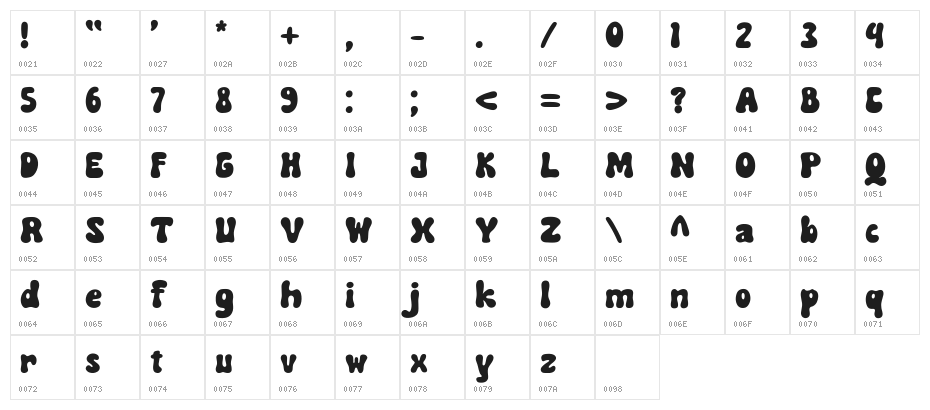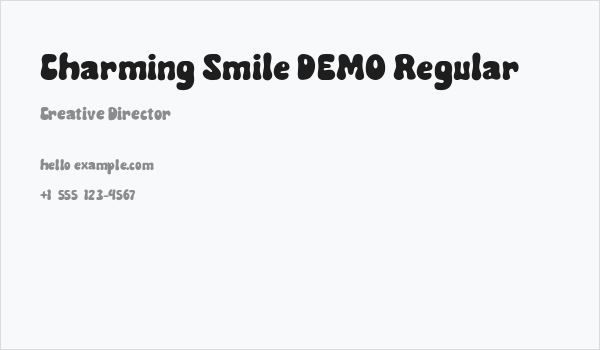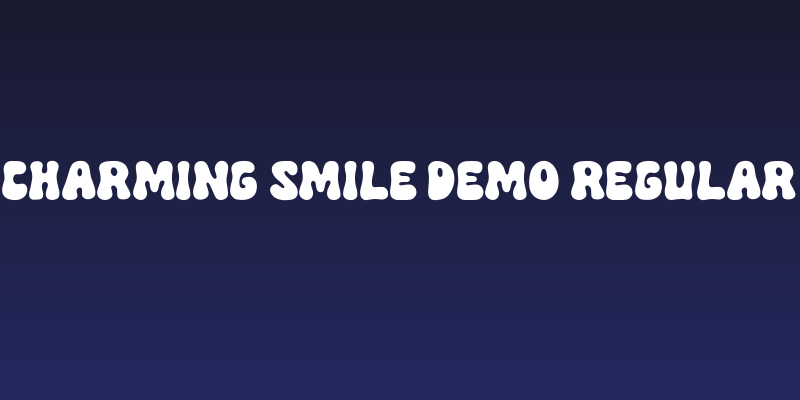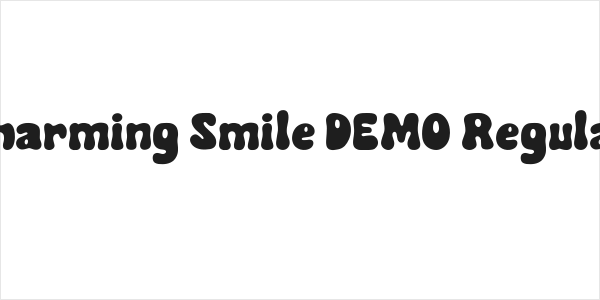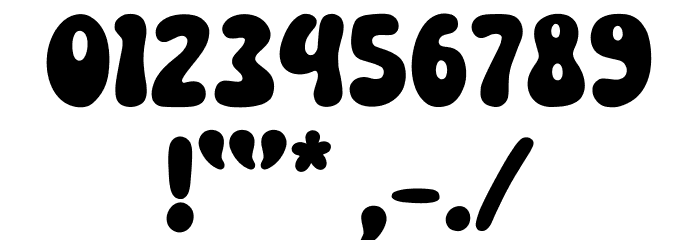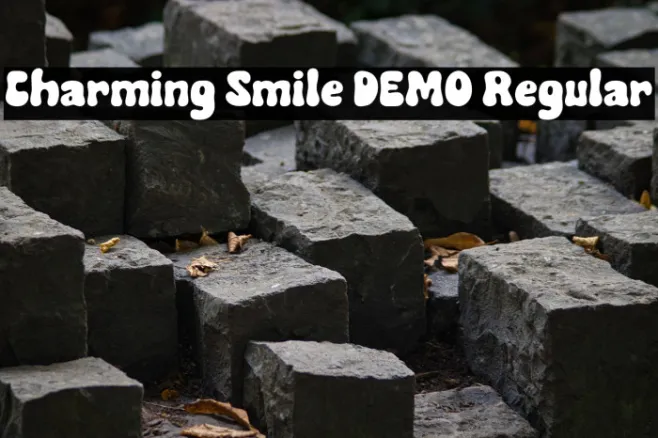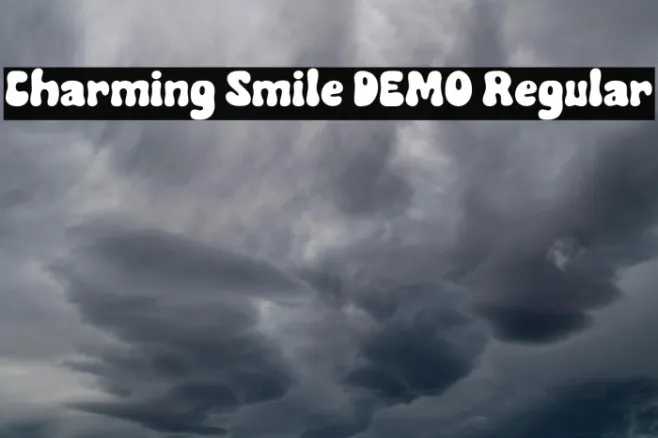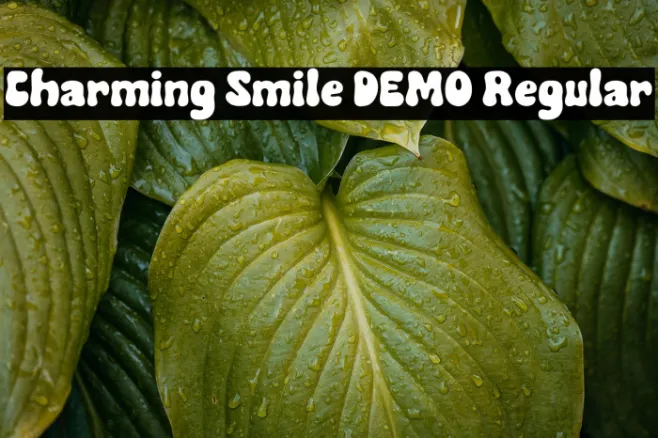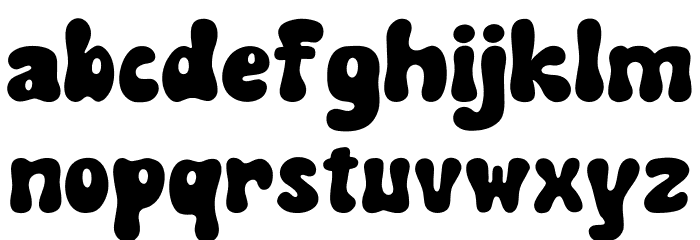
Charming Smile DEMO Regular Font
| Style général | Playful |
| Projets proposés | Ideal for children's books, playful branding, party invitations, and creative posters. |